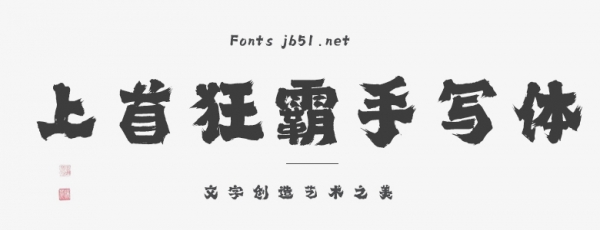
上首狂霸手寫體該字體字體方正工整,筆刷顯著,粗細(xì)變化強(qiáng)烈是此套字庫的亮點(diǎn),具有獨(dú)特性??梢院芎玫膽?yīng)用于文本裝潢、信息展示、網(wǎng)頁設(shè)計(jì)、篆刻制模、數(shù)據(jù)制作、裝潢設(shè)計(jì)、計(jì)算藝術(shù)設(shè)計(jì)、視覺設(shè)計(jì)、字帖等一切合法應(yīng)用場景,有喜歡的朋友可免費(fèi)下載收藏。